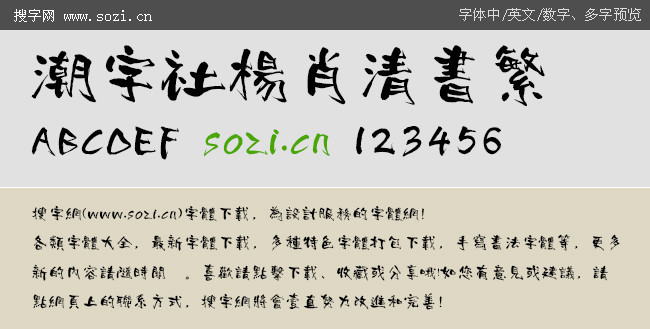
潮字社楊肖清書繁
搜字網(wǎng)提供一款潮字社楊肖清書繁中文字體下載,潮字社楊肖清書字體是由銳字工房開發(fā)設(shè)計(jì)的一款中文手寫字體,該字體筆觸粗細(xì)適中,整個(gè)字體非常流暢自然,大氣中還帶一些時(shí)尚,適用于書籍封面設(shè)計(jì)、報(bào)刊標(biāo)頭設(shè)計(jì),包裝設(shè)計(jì),海報(bào)設(shè)計(jì)等廣告應(yīng)用。(此款為個(gè)人非商用版,如需商用請(qǐng)聯(lián)系銳字工房購(gòu)買)